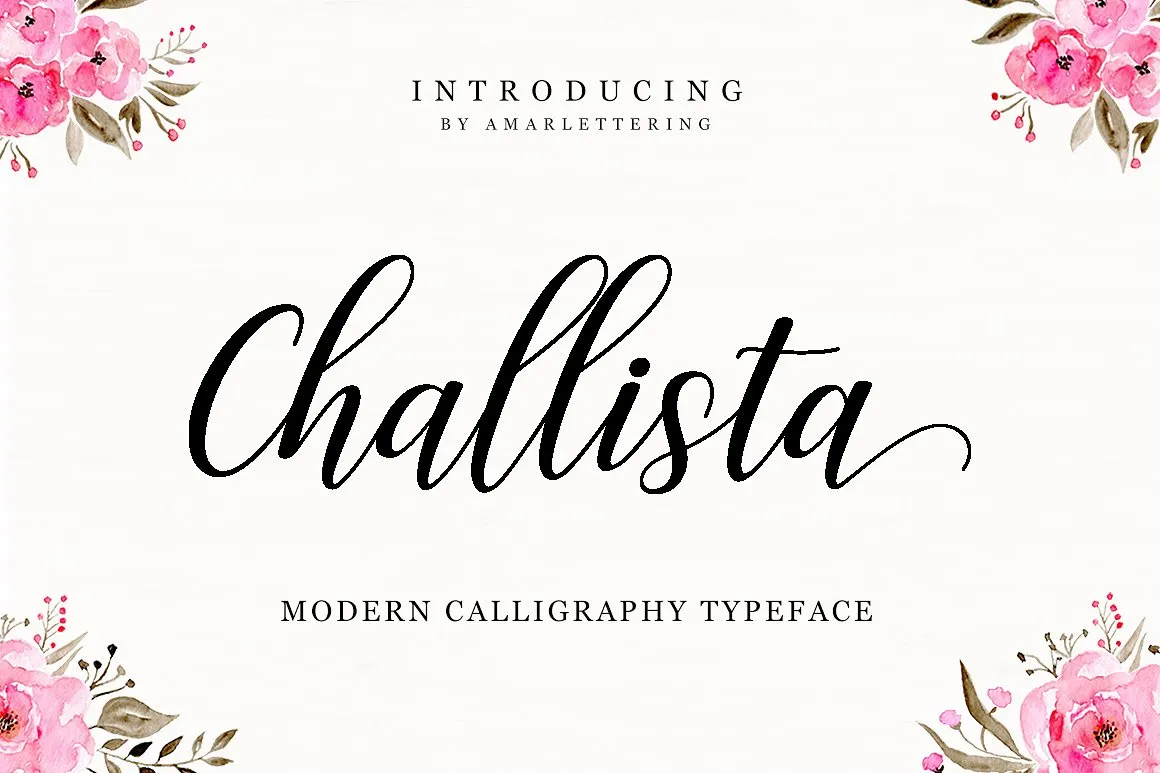
Introduzimos a fonte Challista Script! Desenhada pelo artesão Challista, esta é uma fonte premium disponível na plataforma Creativemarket. Embora ela seja frequentemente vendida lá, está gratuita hoje para download. Challista Script é um novo e moderno estilo de letra cursiva que incorpora elementos de escritura artesanal com caracteres decorativos, além de uma linha base dançante! Esta fonte se destaca incrivelmente em documentos como convites ou cartas de boas-vindas, materiais de marca, cartões de negócios, frases motivacionais e até mesmo panfletos. Seja qual for o uso, Challista Script certamente enriquecerá sua arte digital.